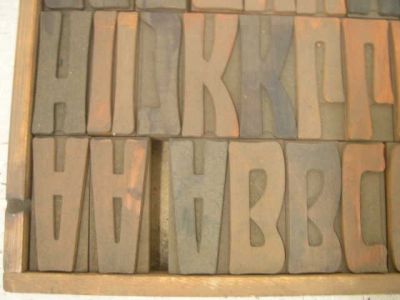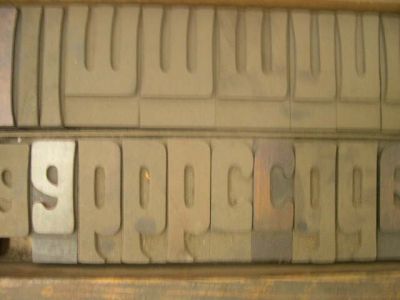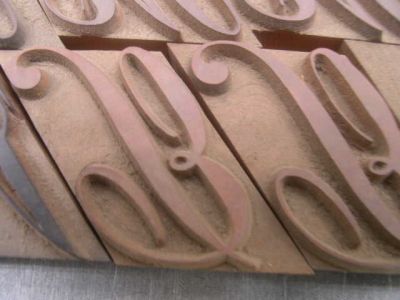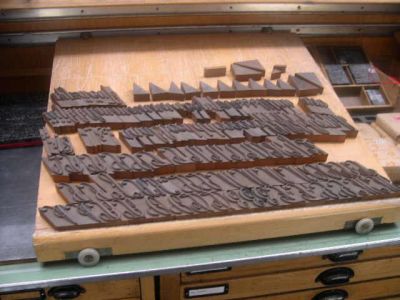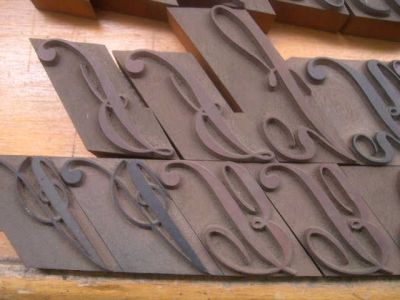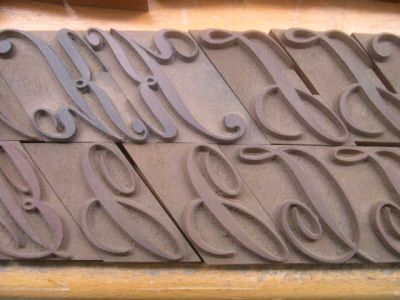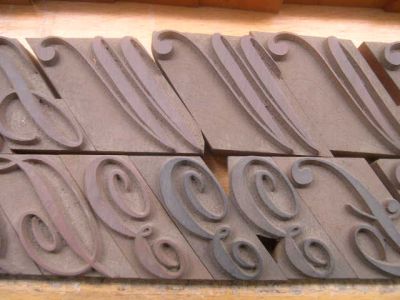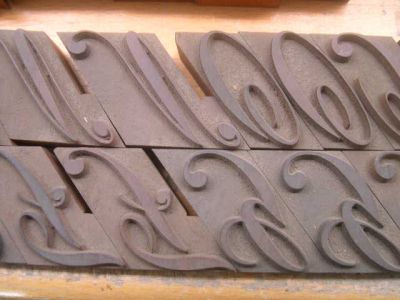
[Mitglied Blei…] Geschrieben Juni 22, 2007 Teilen Geschrieben Juni 22, 2007 ... So, wie es sie auch heute noch überall gibt. In abgesperrten Kellerräumen, Lagern oder - gar nicht selten - in einem verschlossenen Anbau, in dem zwar seit 25 Jahren oder länger nicht mehr gesetzt wird, aber dennoch jede Woche die Putzfrau sauber macht. Irgendwann dann wollen die Druckerfamilien dann doch einmal den Platz anders nutzen. Auch, wenn das Herz daran hängt und man sich sehr bewußt ist, daß drei Generationen damit gearbeitet haben. Fast nie bringt es einer dieser Nachkommen der alten Buchdrucker übers Herz, die Lettern zum Schrotthändler zu geben. Und ich bin immer dankbar, wenn mir ein Kontakt vermittelt wird. Ja, ich weiß: Eigenwerbung. Aber es ist für eine gute Sache. Denn die Schriften kommen so zurück in die Produktion - zu Menschen, die sie lieben und damit neue Gestaltungen produzieren. In Mitteldeutschland waren die Setzereien fast immer mit Schriften der Scdhriftguß A.-G. bestückt. Die bekanntlich nach der Niederlage 1945 im VEB TypoArt Dresden zwangskollektiviert wurde. Meist gab es dort die Super-Grotesk und nicht, wie im Westen und Süden Deutschlands die Futura Buch. Vor allem aber die unglaublich schönen und seltenen Schreibschriften und Antiqua-Varianten der Schriftguß A.-G. Diesen Bestand habe ich heute in Leipzig aufgekauft. Mittwoch und Donnerstag holen wir ihn ab. Ich dachte, es interessiert Euch vielleicht, einmal zu sehen, welches Schriftensortiment eine typische mittelständische Buchdruckerei in Mitteldeutschland früher vorhielt: Manutius 6', 8', 10' Manutius hf 8' Meister 8', 9', 10', 14' Meister hf 9', 14' Meister kursiv 6', 8' Primus 6', 8', 10', 12' Primus hf 9', 14' Primus kursiv 6', 8' Cicero Splendor zart Cicero Prägefest 12', 24', 36', 48' Buch grotesk 6', 8', 10' Buch grotesk mager 9', 12' Buch grotesk hf 6', 8', 10', 12' Belwe kursiv 12', 16', 20', 28' Petit Splendor zart Korpus Splendor zart Splendor 16' Splendor hf 16', 20', 24', 28' Deutschland 36' Isabell 12', 16', 20' Schreibschrift 14', 16', 20' Super schmalfett 16', 36' Super hf 10', 12' Super 3/4fett 14', 16', 20', 24' Super fett 8', 10', 12' Nonpareille breite Koralle Petit breite Koralle Korpus schmalfett Cicero breite Koralle Pergamon mager 16' Rhytmus 6' Technotyp hf 8', 12' Cicero neue Grotesk schmalfett Bernhard Schönschrift Tertia Marggraff-Deutsch Tertia mittel Meister Antiqua schmalfett 20' Perkeo Reporter Bravour 6', 12' Bravour hf Bravour mager 6', 10' Bravour schmal Bravour fett kursiv 6', 8', 12', 16' Elegant Lichtfette Grotesk Typoskript 16', 20', 24', 36' Romanisch mittel Text Venus 6', 8', 10' Venus hf 6', 8', 10', 12', 16', 20', 28' Venus fett 6', 8', 12', 16', 20', 28' Futura 6', 8' Futura hf 8' Antiqua 8', 10', 12' Kurier 14', 16', 20', 28' Schreibmaschinenschrift 10' Didot 6', 8', 10', 12' Didot hf 16', 20' Georg Link zu diesem Kommentar
[Mitglied Schm…] Geschrieben Juni 23, 2007 Teilen Geschrieben Juni 23, 2007 Uff, Bernhard Schönschrift Tertia, die hab ich in Blei, wieso auch immer. Den Rest kauf ich ungesehen (irgendwann mal) dazu. Liebe Grüße, Schmorkohl Link zu diesem Kommentar
[Mitglied Blei…] Geschrieben Juni 27, 2007 Themen-Ersteller Teilen Geschrieben Juni 27, 2007 Heute und morgen holen wir die Setzerei in Leipzig ab. Genauer: Ich organisiere, zwei "Jungs für's Grobe" fahren hin. Das sind 9 Satzschränke und sie stammen alle aus der Vorkriegszeit. Nach dem Krieg wurde damit natürlich bis in die 70er Jahre hinein auch noch gesetzt, aber dann schon sehr früh umgestellt auf Offset. Ab wann gab es eigentlch Fotosatz in der DDR? Und welche Systeme? Wer kann mir das sagen? 9 Schränke: 4 Einzelschränke mit Brotschriftgraden (siehe Photos) 3 Doppelschränke (Brotschriften und Steckschriften) 2 Stehsatz-Regale, komplett gefüllt mit Sehsatz-Formen Zusätzlich ca. 800 kg Blindmaterial (Quadraten, Regletten, Hohlstege), ca. 300 Galvano-Klischees, 3 komplette Holzlettern-Schriftschnitte, einer eine Fraktur in 8 Cicero, 10 Cicero und 12 Cicero. Donnerstagabend kommen die Jungs wieder. Freitag bin ich dann alleine mit dem Schatz und feiere Bescherung. Das ist (für mich) jedesmal ungemein aufregend, wenn ich so einen Bestand das erstemal durchsehe. Die Druckerei, aus der dieser Bestand kommt, wechselte nach der Wiedervereinigung dreimal den Besitzer. Keiner interessierte sich für den Satz, der weiterhin in einem Kellerlager schlummerte. Das ist gut, denn das bedeutet, daß vielleicht keine Grabräuber gehaust haben, um Rosinen zu picken. Dort steht auch noch ein Papierschneider, Marke Mansfeld, Baujahr 1926. Die nehmen wir aber nicht mit wegen des hohen Gewichtes. Sie wird getrennt von einem Partner von mri abgeholt, der sich auf die Restaurierung alter Druckmaschinen und solcher Schneidemaschinen spezialisiert hat. Georg Link zu diesem Kommentar
[Mitglied Blei…] Geschrieben Juni 30, 2007 Themen-Ersteller Teilen Geschrieben Juni 30, 2007 Allererste Ergebnisse: Jugendstil- und Schreibschrift-Holzlettern. Größe: 12 Cicero, 16 Cicero - ungesäubert mit dem Staub aus vielen Jahrzehnten: Link zu diesem Kommentar
[Mitglied Norb…] Geschrieben Juni 30, 2007 Teilen Geschrieben Juni 30, 2007 Oooooooh .... Link zu diesem Kommentar
[Mitglied Flor…] Geschrieben Juli 4, 2007 Teilen Geschrieben Juli 4, 2007 Uuuuuhhhh Ooooohhh Solche Holzlettern würde ich glatt an die Wand hängen … Glückwunsch! Link zu diesem Kommentar
[Mitglied Blei…] Geschrieben Juli 4, 2007 Themen-Ersteller Teilen Geschrieben Juli 4, 2007 Komplett... Link zu diesem Kommentar
[Mitglied Norb…] Geschrieben Juli 4, 2007 Teilen Geschrieben Juli 4, 2007 Die würde ich nicht an die Wand hängen, das wär mir zu schade, damit würde ich drucken wollen (wenn ich's denn könnte), notfalls stempeln, auch wenn im Ernstfall nicht mehr als ein Geschenkeinwickelpapier dabei herauskäme ... Link zu diesem Kommentar
[Mitglied Ivo…] Geschrieben Juli 8, 2007 Teilen Geschrieben Juli 8, 2007 Die Maschine ist jetzt schon demontiert und auf Paletten gelagert.Und geht wohl innerhalb der nächsten Wochen nach Bremen. Ich kann den neuen Eigentümer alles fragen, was Du wissen möchtest. Er kann mir sicher auch ein Photo vom Typenschild mit Maschinennummer zusenden. Das wird aber mit Sicherheit Ende August werden. Naja, so viel Aufwand muss nicht unbedingt sein. Falls es sich ergibt würde ich mich freuen, falls nicht werde ich es auch überleben. Aber danke für das Angebot, Georg. Link zu diesem Kommentar
[Mitglied Blei…] Geschrieben Juli 11, 2007 Themen-Ersteller Teilen Geschrieben Juli 11, 2007 Auf mich als Westdeutschen wirkt diese Dose Elasan regelrecht nostalgisch. Stammt sie aus den 60er oder den 70er Jahren? Ist das so etwas, was bei uns im Westen Nivea war? Georg Link zu diesem Kommentar
[Mitglied Robe…] Geschrieben Juli 11, 2007 Teilen Geschrieben Juli 11, 2007 florena war unsere nivea. halt nein, sie ist es natürlich noch. das andere kenn ich nicht, vielleicht gleitcreme für bleiläuse? Link zu diesem Kommentar
[Mitglied Blei…] Geschrieben Juli 11, 2007 Themen-Ersteller Teilen Geschrieben Juli 11, 2007 Gab es nur die eine Marke? Sieht aus wie Nivea - von außen. Kennst Du dieses Elasan? Ist vom VEB Leipziger Arzneimittelwerk. Oder stammt das vielleicht aus einer Zeit, als Du noch gar nicht existent warst? Ward Ihr auch so ein VEB? Oder waren das immer nur Großbetriebe? Es gab doch auch kleine Selbständige, richtig? Die riecht komisch, die Elasan. Ich meine, war ja keine Creme mehr drin, nur 10 p Gevierte. Aber die rochen auch nach Salbe irgendwie. Da waren Unterlagen in den Schränken über Klischee-Eingang und -Ausgang. Und so eine Art Auftragsbücher, welcher Kunde wann periodisch mit neuen Formularen und so beliefert werden mußte. Die waren alle aus der Futura gesetzt. Ein Skatspiel war auch dabei. Aber leider in Dortmund gedruckt. Ist ein eigenartiges Gefühl, den Nachlaß von alten Setzern zu durchstöbern. Neben anderen auch ein Paket mit vertikal gestrichelten 4 p Messinglinien inkl. Gärungsstücken Die verkaufe ich aber nicht, die schenke ich MZS bei seiner nächsten Bestellung. Die Dose behalt ich. Ich hatte noch nie so ein DDR-Ding. Meine Verwandschaft kommt ja nicht aus Mitteldeutschland, sondern aus Ostdeutschland. Da, wo heute Polen ist. Georg Darf man das eigentlich sagen, daß Ostdeutschland heute Polen ist? Oder ist das verboten? 1 Link zu diesem Kommentar
[Mitglied Blei…] Geschrieben Juli 11, 2007 Themen-Ersteller Teilen Geschrieben Juli 11, 2007 Vielleicht ist die Creme vergoren ? Ich schmeiß das Ding sofort weg morgen. :x Da will man mal freundlich sein und ohne Vorurteile an so eine blöde Creme aus der DDR herangehen. Das hat man nun davon. Link zu diesem Kommentar